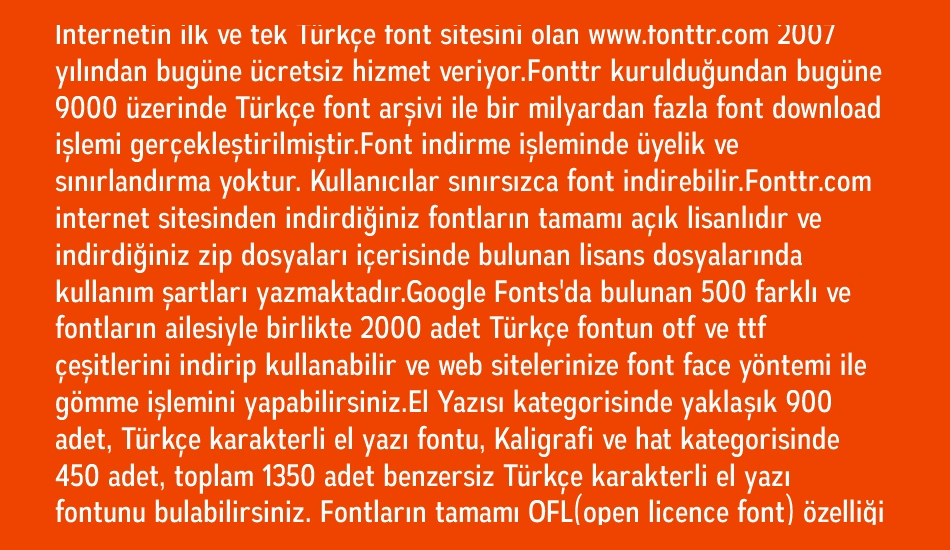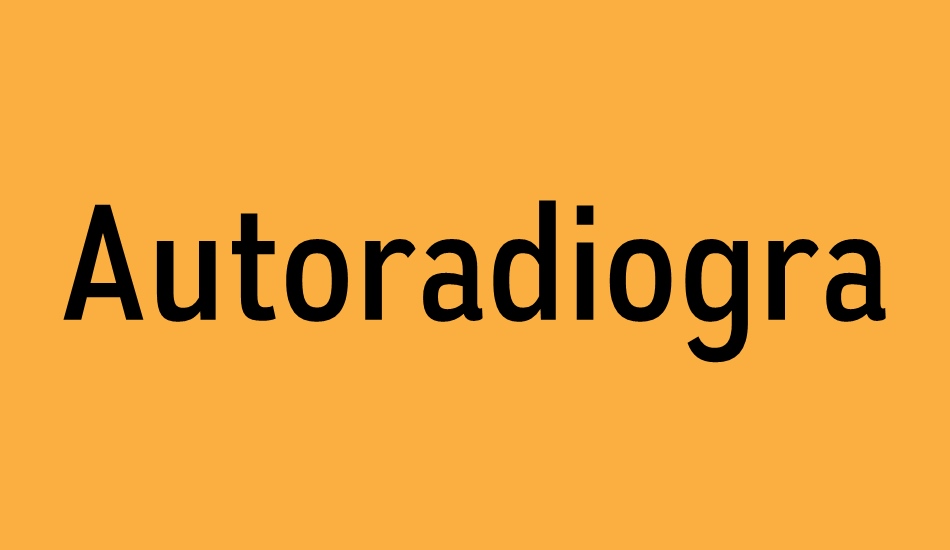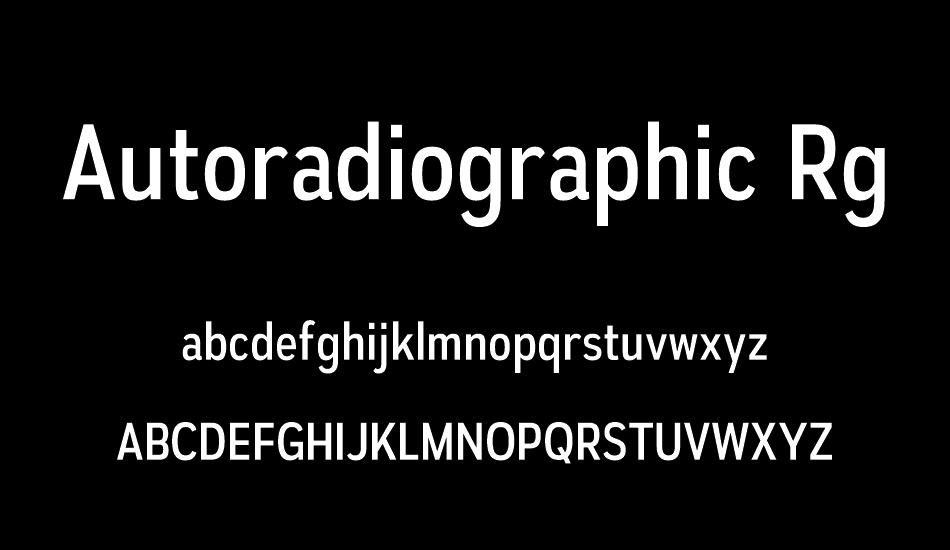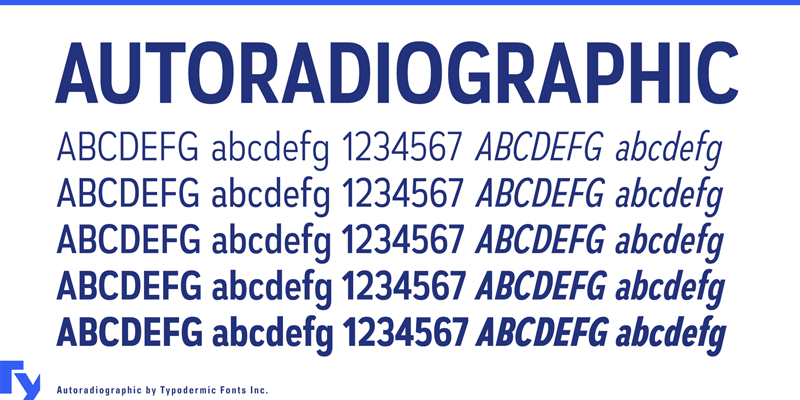
Autoradiographic font
Autoradiographic, yirminci yüzyılın ortalarında elle boyanmış uyarı işaretlerine esin kaynağı olan 5 ağırlıkta sans-serif bir yazı biçimidir. Parlayıcı! Dışarıda tutmak! Savaş sonrası düşük bel çizgileri bu yıllarda şıktı, ancak bel düzeni hizasında değildi. Bu türden bilgilendirici yazıların temiz ve teknik olması amaçlandı, ancak bazı kişilik parlıyordu. Autoradyografik, Kiril, matematik sembolleri, kesirler ve en son para simgelerini içerir. İtalikler dar ve gevşek olarak ekstra vurgu yapmak için aralıklarla yerleştirilir. Düzenli ve italik stiller için masaüstü lisansı ücretsizdir.
Autoradiographic Rg font